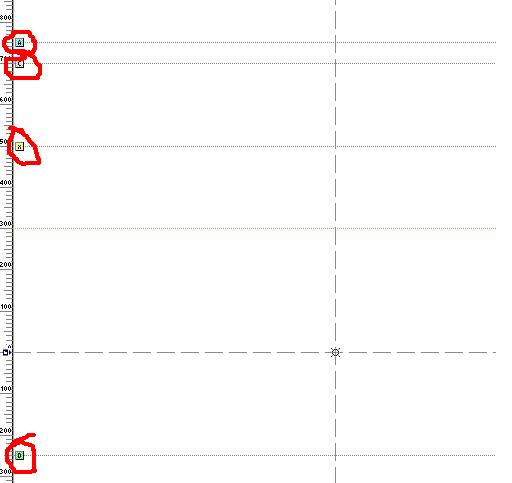
ถามเรื่องเส้น A,D,X,C ใน Fontlab :
เส้น A,C,X,D พวกนี้มีไว้ทำอะไรครับ มีประโยชน์อย่างไรครับ แล้วเราจะใช้งานมันอย่างไรครับ เพราะผมลองปรับเล่นๆดูมันก็ไม่สามารถปรับได้เลยครับ ผู้รู้ช่วยตอบทีครับ ผมค้นกระทู้เก่าๆดูก็ไม่เจอ รบกวนช่วยบอกทีครับ ขอบคุณครับ
A = Ascender
D = Descender
x = x height
C = Cap height
A คือส่วนที่สูงที่สุดของพื้นที่ตัวพิมพ์
D คือส่วนที่อยู่ต่ำที่สุดของพื้นที่ตัวพิมพ์
x คือความสูงของตัวพิมพ์เล็ก
C คือความสูงของตัวพิมพ์ใหญ่
ถ้าอยากปรับได้ ให้เข้าไปที่ view > Lock Layers > Vertical Metrics ติ๊กออกก็ปรับได้แล้วหละ